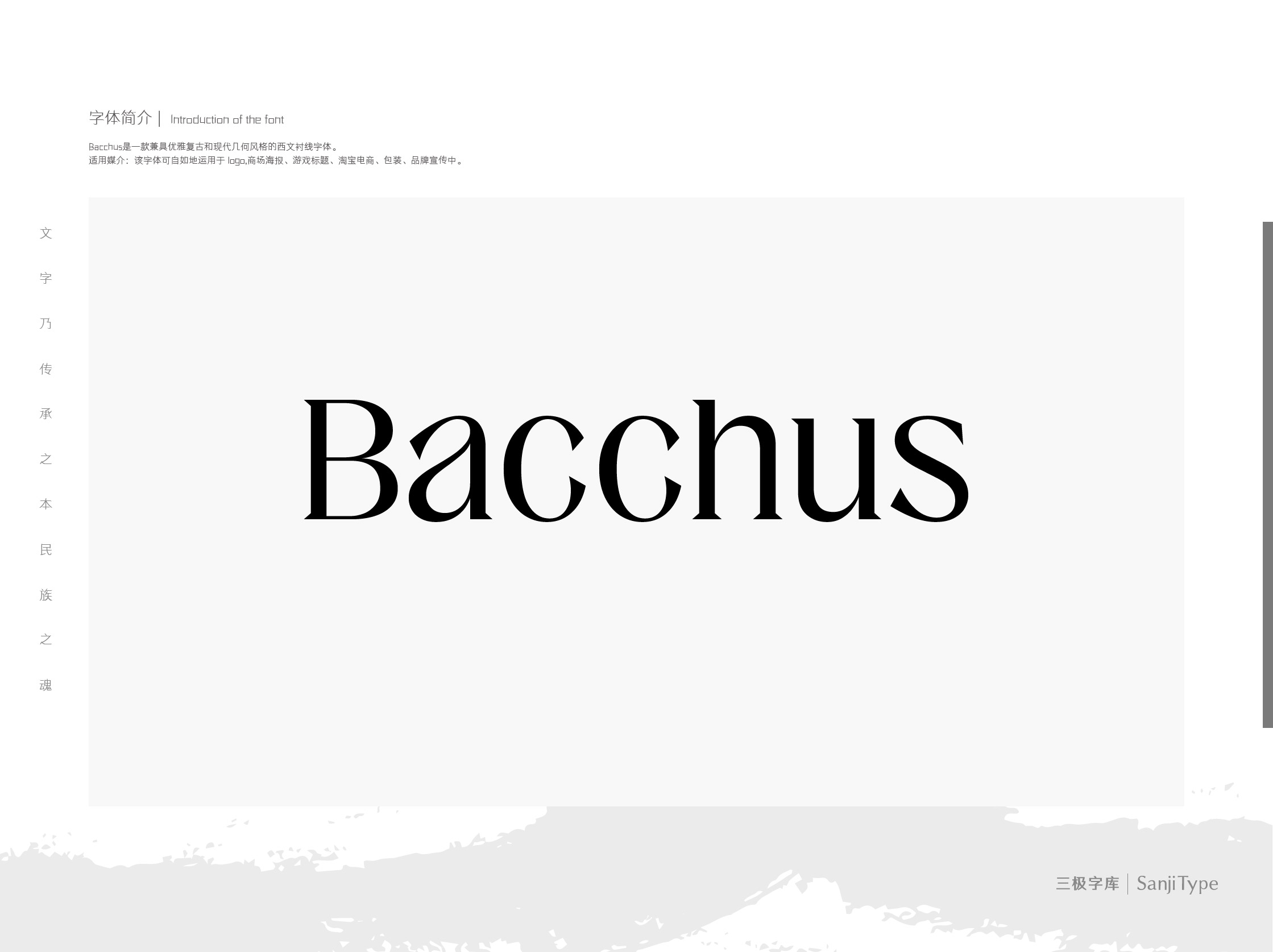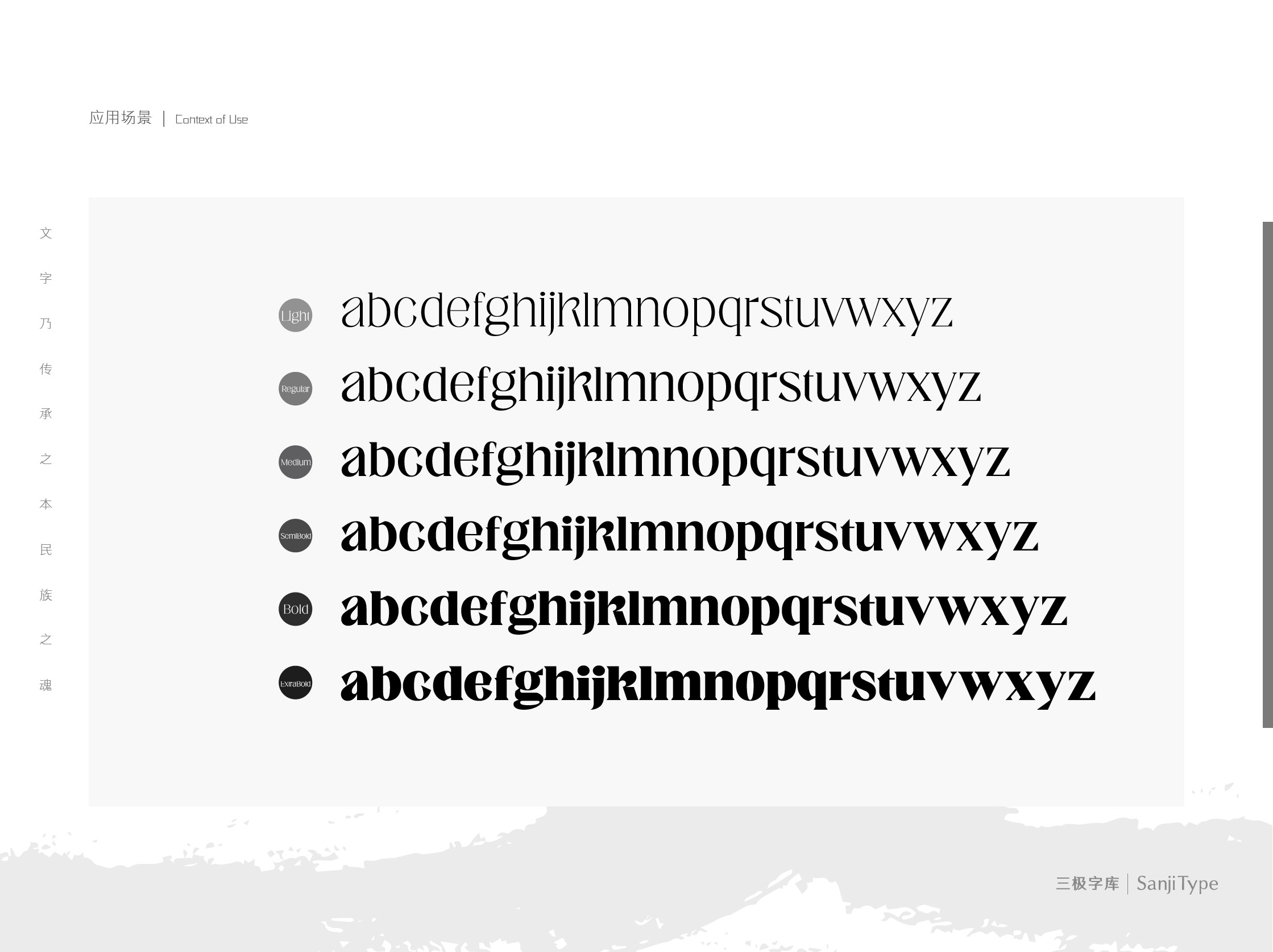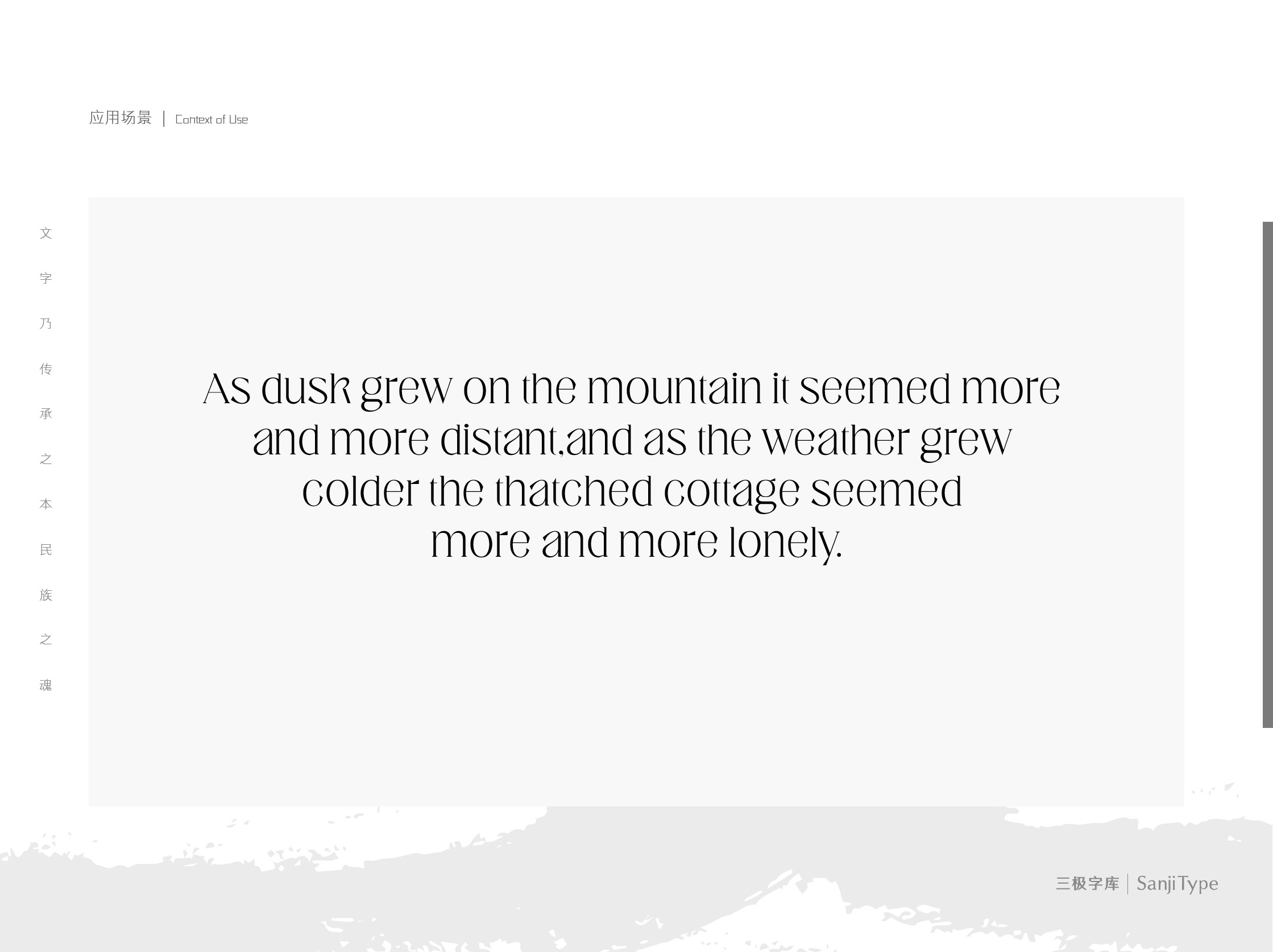
Bacchus家族
Bacchus是一款多字重的衬线体,兼具优雅复古和现代几何风格。几何形状修整成衬线装饰,带出尖锐的现代几何感。同时又不减损其稳重和精致。缓慢的圆形曲线与轻快、尖锐的衬角舒适地融合。笔画粗细对比强烈,遵循横细竖粗的原则,笔画连接处亦带有粗细过度变化。该字体可自如地运用于 logo,商场海报、游戏标题、淘宝电商、包装、品牌宣传中。